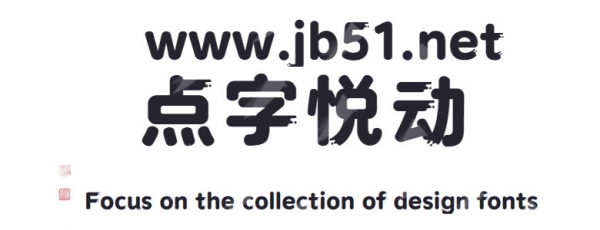
點(diǎn)字靈動(dòng)體是由點(diǎn)字庫(kù)推出的藝術(shù)字體,字體字的收筆處做了特殊設(shè)計(jì)處理,圓點(diǎn)的流動(dòng)性配合,顯得字體自然有趣味,適合應(yīng)用于藝術(shù)設(shè)計(jì)、各類(lèi)廣告和產(chǎn)品包裝設(shè)計(jì)等領(lǐng)域。
這款字的收筆處做了特殊設(shè)計(jì)處理,圓點(diǎn)的流動(dòng)性配合,顯得字體自然有趣味。適用于品牌的廣告、產(chǎn)品包裝設(shè)計(jì),多媒體等視覺(jué)平面作品中。